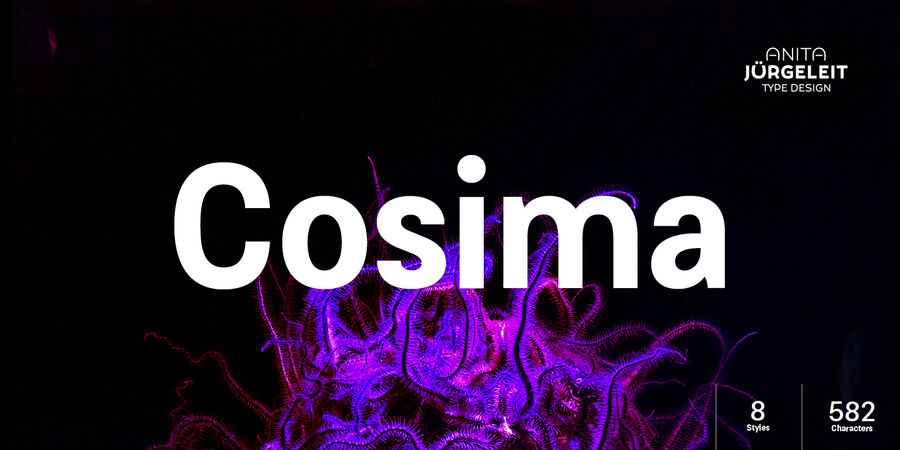
Cosima (8 шрифтів)
Опис гарнітури CosimaШрифт Cosima – ефективна робоча конячка з відтінком тонкої елегантності. При запуску нового бренду або створенні користувацького інтерфейсу для мобільних пристроїв дуже важливий вибір характерного шрифту. Також для журналів і сайтів типографія завжди є найважливішою частиною дизайну.
Зрізи штрихів Cosima, розташовані вертикально та горизонтально, роблять шрифт міцним і стійким. Звужені символи та збільшена висота рядкових літер елегантно впливають на вигляд тексту й показують цікаві деталі на великих розмірах.
Шрифт розробила Аніта Юргелайт в 2019 році.
Асоціації з сімейством шрифтів CosimaОсобистість і характер гарнітури:
делікатний, чистий, легкий, худий, прохолодний, тонкий, сучасний, ясний, рівний, якісний, невагомий, прозорий, міський, мінімалістичний, чіткий, інтимний, крихкий, повітряний, скляний, статичний, лаконічний, розумний, точний, дротяний, свіжий, економний, економічний, логічний, глобалізований, глобалістічний, діловий, формальний, елементарний, самостійний, відповідальний, західний, переконливий, прямокутний, стабільний, Простий, нейтральний, монотонний, твердий, серйозний, стійкий, інженерний, техногенний, різкий, креслярський, комп'ютерний, урбаністичний, прагматичний, практичний, доступний, залізний, сталевий, надійний, впевнений, машинний, індустріальний, обов'язковий, важливий, архітектурний, сильний, робочий, мотивуючий, залізничний
дієта, гігієна, дизайн, Місто, чистота, наука, хімія, математика, урбаністика, код, креслення, конструктор, інженер, автоматика, андроїд, IT, айтішник, комп'ютер, електроніка, програмування, айті, технології, прилад, інновації, коворкінг, архітектура, небо, інструмент, промисловість, техніка, залізо, рентген, вода, верстат, тара, електростанція, енергетика, машинобудування, завод, автомобіль, мотор, прес, шолом, уніформа, вагон, будівництво, робот, космос, фантастика, гаджет, девайс, паливо, архітектор, новини, бізнес, комп'ютерна гра, астрономія, залізниця, робочий Гарнітура асоціюється з віком: